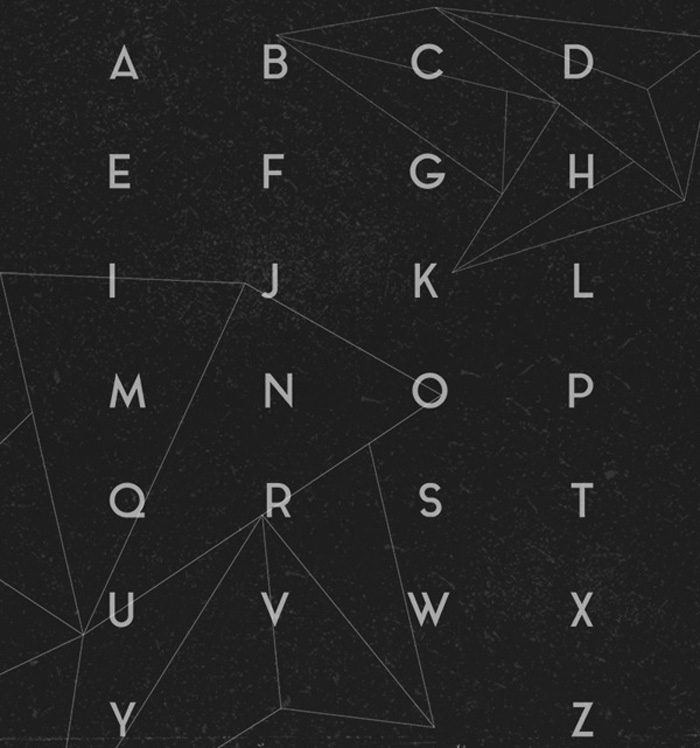
La diseñadora gráfica Laura Pol ya pasó por oldskull a enseñarnos sus buenísimos trabajos. Hoy nos regala esta bonita fuente tipografía llamada Aqua Grotesque e inspirada en las tipografías de los años 40/50. ¡A descargar!